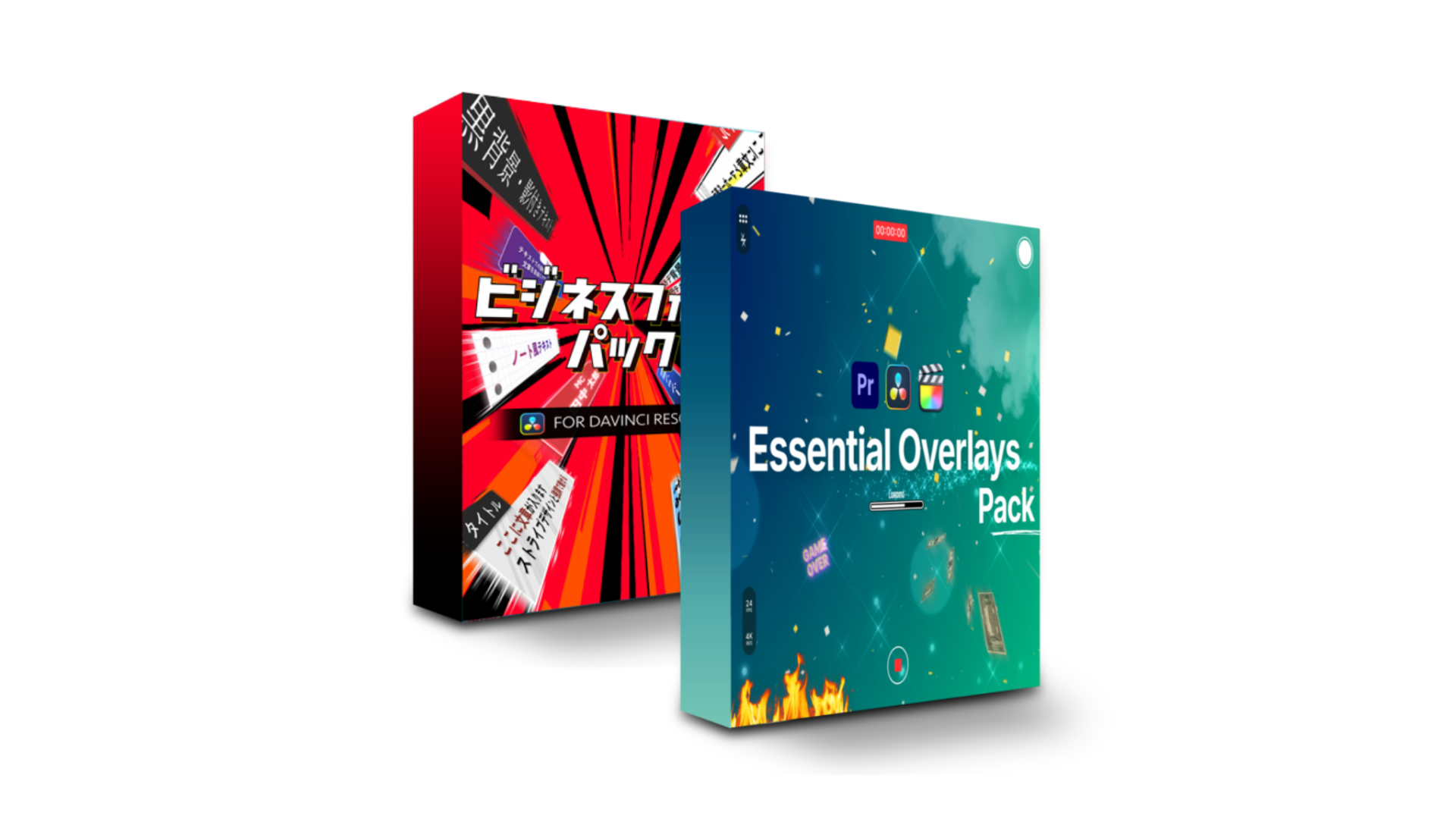
Business Font Pack、Essential Overlays Packの販売を開始
Visual Park、動画編集を加速させる2つの新作パックを販売開始
Visual Parkは本日、ビジネス・教育・エンタメ動画に向けたDaVinci Resolve用テンプレート集「Business Font Pack」と、あらゆる編集ソフトで使用可能な高品質演出素材集「Essential Overlays Pack」の提供を開始しました 。
計300種類を超える洗練されたアセットにより、クリエイターは編集時間を大幅に短縮しながら、メッセージの伝わりやすさと視覚的なインパクトを両立させることが可能になります 。これらのパックは、企業のプロモーション動画からSNSコンテンツまで、現代の映像制作に求められる高いクオリティを即座に実現するために設計されています 。
Business Font Pack
新しいBusiness Font Packは、ビジネスシーンに求められる清潔感と信頼性を兼ね備えた195種類のタイトルテンプレート、7種類のエフェクト、4種類のトランジションを収録し、動画制作の効率を飛躍的に向上させます 。Visual Parkオリジナルの「VisualParkObliqueV1/V2」といった高品質な日本語フォントが同梱されています 。これにより、インストール後すぐに洗練されたデザインのテロップを使用することが可能です 。
Essential Overlays Pack
映像制作のクオリティを瞬時に引き上げるオーバーレイ素材集「Essential Overlays Pack」が、Visual Parkよりリリースされました 。炎、煙、光のフレアから、手書き風のマーカー、グリッチ、カウントダウンまで、合計118種類の多彩な素材をラインナップしています 。
矢印アニメーション(8種)や紙吹雪、雨、雪などの自然エフェクト、さらにはiPhone録画風の画面レイアウトなど、実用性の高い素材が揃っています 。個人のYouTube動画から商用プロジェクトまで、幅広い用途で活用いただけます 。